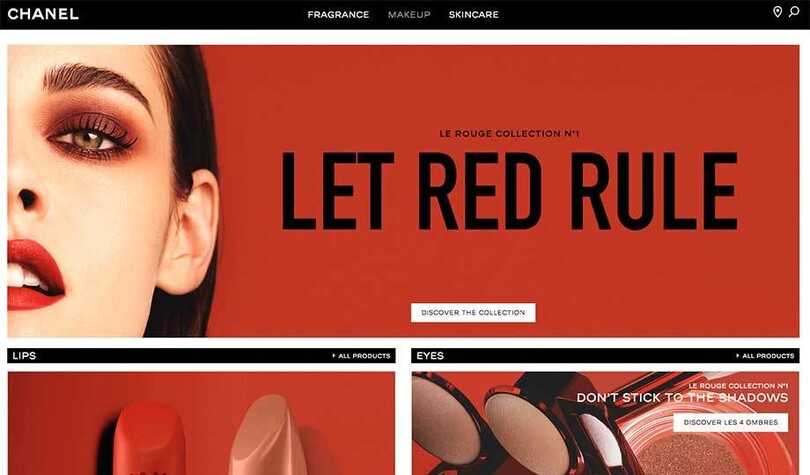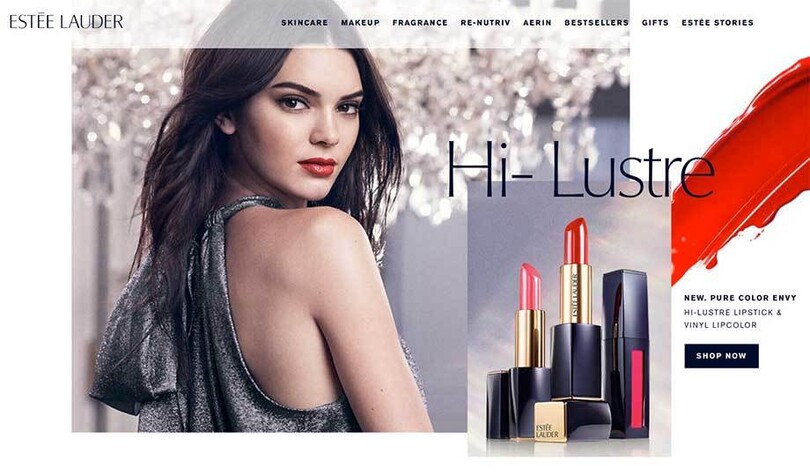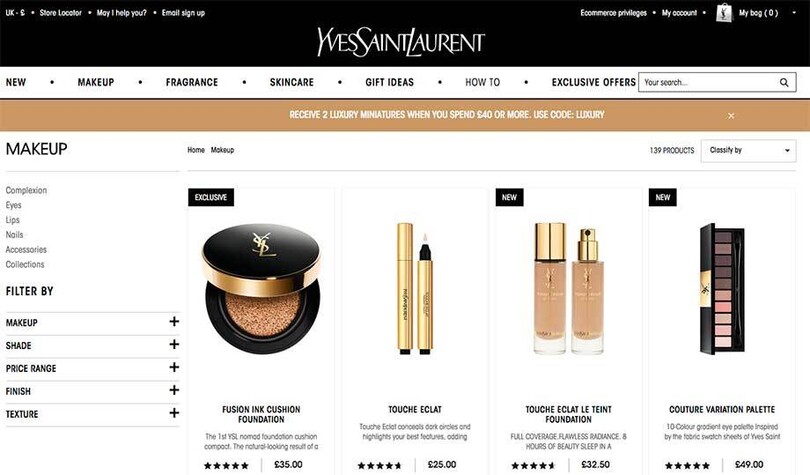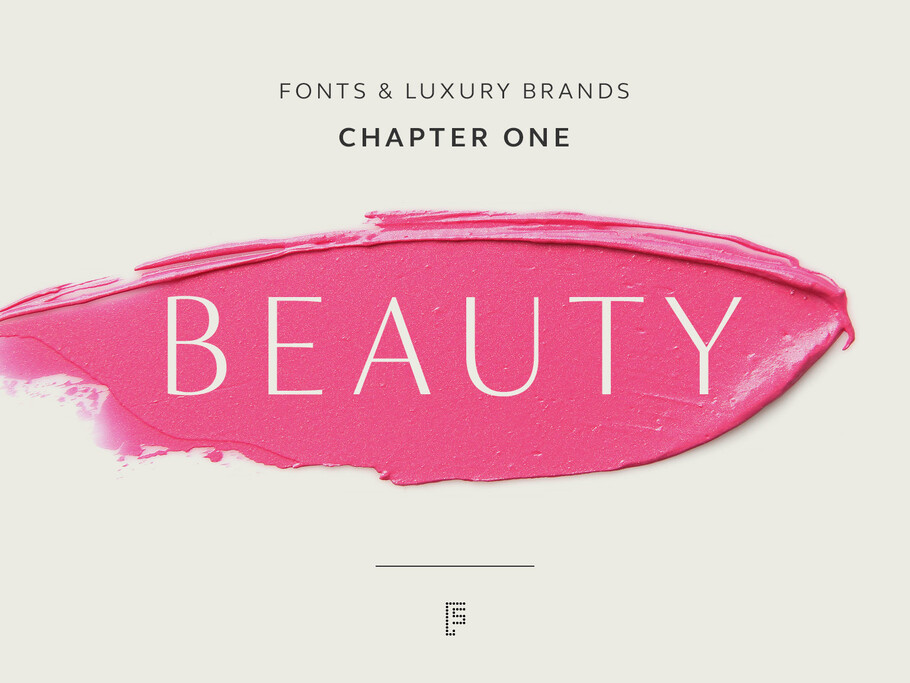
Fonts und Luxusmarken: Beauty-Branche.
Es gibt bestimmte Fontmerkmale, die traditionell als Zeichen für Luxus angesehen werden, wie Serifen und kontrastreiche Striche.
Wir wollten die Top-Luxusmarken aus den Bereichen Beauty, Fashion, Automobil und Reisen untersuchen, um herauszufinden, welche Schriften diese Marken verwenden und wie. Nehmen wir zuerst den Beauty-Sektor – verwenden wirklich alle Beauty-Marken Optima? Wir haben uns zehn der Top-Marken angesehen und dabei einige Überraschungen entdeckt.
Clarins
Die primäre Schrift von Clarins ist eine kontrastreiche Serifenschrift, die Baskerville ähnelt. Eine elegante Schrift, perfekt für die Darstellung von Beauty-Produkten. Die Marke verwendet viele weiße Räume und der Clarins-Font wird für große Bildtexte und Gotham SmartScreen für Text und Fließtext verwendet.
Lancôme
Das Thema der starken Kontraste setzt sich bei Lancôme fort. Haarscharfe dünne Striche der verwendeten Garamond-Version vermitteln ein Gefühl von höchster Qualität. Für die Navigationsleiste auf der Website wird Garamond in Großbuchstaben gesetzt, für große Bildtexte dagegen in Klein- und Großbuchstaben. Gotham wird auch für Fließtext verwendet. Durch die Verwendung von Schwarz wird das Kontrastmotiv noch verstärkt, und Farbe wird nur spärlich eingesetzt.
Clinique
Clinique hat einen einzigartigen Stil. Ihr Logo-Font ist eine leicht zittrige Serife namens Jorvik Informal, die kontrastreich und ziemlich ungewöhnlich ist. Durch die Kombination mit Helvetica, Leerraum und Pastellfarben entsteht eine einzigartige Marke in der Kosmetikbranche. Sauber, modern, frisch und stilvoll. Sehr einfach, aber äußerst effektiv.
Estēe Lauder
Optima ist eine kontrastreiche Sans-Schrift, die Eleganz und Stil ausstrahlt und wunderschön gestaltet ist. Klassische Proportionen, klar, lesbar, dezent und eine große X-Höhe. Estēe Lauder verwendet den Font in einer leichten Schriftstärke, die zusammen mit großen Bildern und der Markenfarbe Marineblau einen formellen, seriösen, aber kultivierten Eindruck vermittelt.
Shiseido
Reader Bold hat große Ähnlichkeit mit Gotham und wird in Großbuchstaben für das Navigationsmenü verwendet. Auch hier wird Schwarz auf Weiß als Motiv eingesetzt. Die Exklusivschrift Shiseido2013 wird für Fließtext und kleine Details verwendet und ähnelt Optima insofern, dass es sich um einen kontrastreichen Sans mit einer großen X-Höhe, einer großen offenen Punze und einem breiten Ton handelt. Auf ihrer Website sind uns einige Probleme bei der Textausrichtung aufgefallen, darunter große Lücken bei Text im Blocksatz, eine verwirrende Mischung aus zentriertem und linksbündigem Text sowie Text im Blocksatz und auch Überschriften, die nicht mit dem Haupttext übereinstimmen.
YSL
ITC Avant Garde Gothic Condensed ist eine Abweichung vom gängigen, überstrapazierten Gotham. Es handelt sich um eine schmale, geschlossene Schrift, die nicht sehr gut lesbar ist. Dies ist das einzige untersuchte Beauty-Produkt mit einem schmalen Primärfont. Die ITC Avant Garde Gothic Standard Version, eine geometrische und monolineare Version, wird groß und fast in Postergröße verwendet, wodurch ein starkes, dominantes Gefühl entsteht, das dem Logo oder der Marke im Sinne der Finesse nicht sehr zuträglich ist.
Chanel
Der starke, kühne geometrische Sans-Font, im Logo ganz in Großbuchstaben gesetzt, verkörpert Eleganz und Klasse – ein Synonym für die Marke Chanel. Die Typografie der Marke verwendet eine umbenannte Version von Gotham und bleibt unveränderlich. Alles ist fett und ganz in Großbuchstaben gesetzt, mit Ausnahme des kleinen Fließtextes, der in Helvetica ist. Die maskulinen und femininen Bereiche sind nur durch Farbe und Bildsprache getrennt.
Tom Ford
Auf der Website von Tom Ford können wir den Satz vollständig in Großbuchstaben sehen und wieder ein schwarz-weißes Motiv – ohne Kleinbuchstaben. Stark, mutig und modern – das spricht die jüngeren Märkte an, die Schneid und Stil brauchen. Sehr maskulin und dominant.
Givenchy
Givenchy ist eine französische Luxusmarke, die für ihr schickes und kreatives Design bekannt ist. Die Marke ist überwiegend bildbasiert, aber auf der gesamten Website werden für die Bildtexte, und einige Texte, durchgängig Großbuchstaben verwendet. Außerdem ist Sackers Gothic Light eine breite, monolineare Großbuchstabenschrift mit überdehnten Formen. Auch Apercu wird hauptsächlich in Großbuchstaben verwendet, ein schlanker Grotesque-Sans mit schmalen Proportionen im Gegensatz zum quadratischen Givenchy-Emblem.
Bobbi Brown
Das Logo von Bobbi Brown ist in Univers Ultra Condensed gesetzt, und es ist die einzige Marke, die schmale Proportionen in ihrem Logo verwendet. Sie verwenden viel weißen Raum mit schwarzer Schrift und schwarzen Rändern, was einen strengen, harten Tonfall erzeugt. Einem lockeren Handschrift-Font, der einige Inhalte ziert, fehlt es an Finesse, da die fetten Formen plump und undefiniert wirken. Die Verwendung von Brandon Text, einem geometrischen, abgerundeten Sans-Font, verleiht der Schrift einen weichen Charakter, wirkt aber in den verwendeten Größen etwas unscharf.
Übersicht und Trends
Kühne Eleganz
Es ist ein Irrglaube, dass Beauty-Marken in ihrer Bildsprache nur zarte Serifen, feminine Farbpaletten und glamouröse Models verwenden. Wir haben nämlich festgestellt, dass es viele monochrome, fette Stile und Großbuchstaben gibt – nicht nur für die Logos, sondern auch für die Website-Navigation und sogar für Fließtext. Vollständig in Großbuchstaben gesetzter Text wirft viele Fragen zu Barrierefreiheit und Lesbarkeit auf, da er nicht nur optisch ablenkt, sondern auch wirkt, sondern auch aufdringlich zu sein scheint. Es ist sehr überraschend, dass einige Marken wie Tom Ford auf ihren Websites überhaupt keine Kleinbuchstaben verwenden. Es ist weniger überraschend, aber interessant zu beobachten, dass fast jede Marke in ihrem Logo nur Großbuchstaben verwendet. Etwas mehr als die Hälfte der von uns untersuchten Marken verwenden in ihrem Logo einen Font mit hohem Kontrast (ähnlich wie Optima), was keine Überraschung ist. Die anderen 40 % verwenden jedoch eine fette, geometrische oder groteske Schrift, die einen ganz anderen Eindruck vermittelt. Außerdem verwenden 40 % eine kontrastreiche Serifen- oder Sans-Schrift als Hauptschriftart, und immerhin 7/10 verwenden einen geometrischen Font.